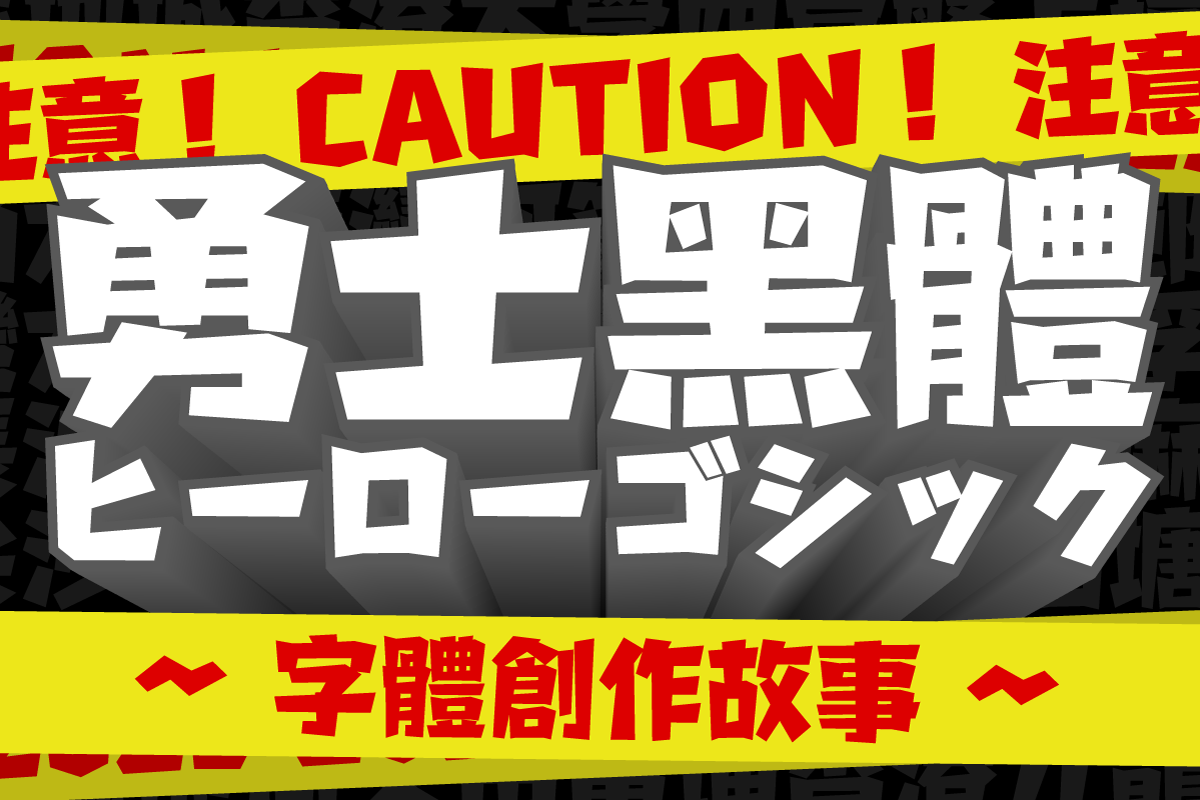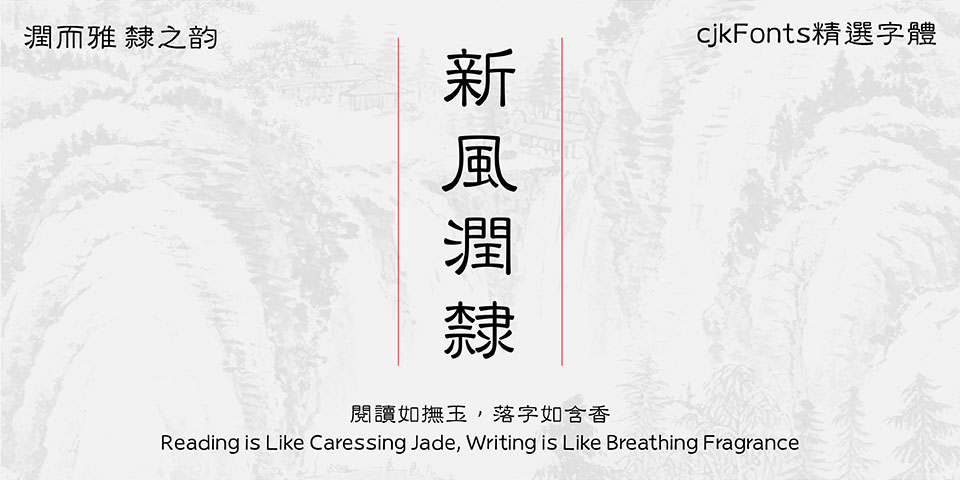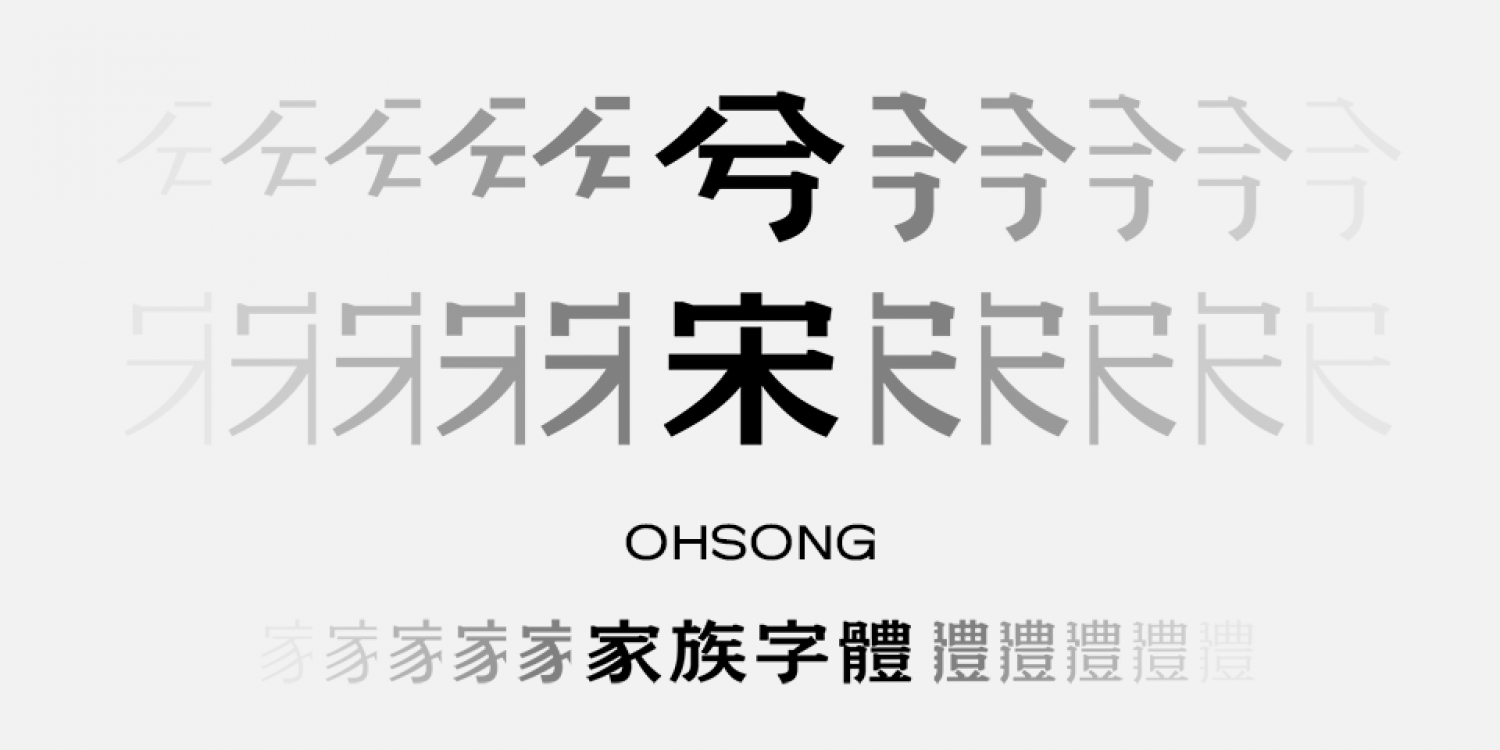
新風潤隸 - 閱讀如撫玉,落字如含香
兮宋家族字體計劃
字言字型免費中文字體1—手繪體
字體採用了手繪塗鴉風格,並以宋體的筆形配上楷體的骨架製成,營造出不同於其他單一風格的造型。
隨峰體Plus
cjkFonts的字型設計師以隨峰體爲基礎,整合不同的衍生版本,並再添補和修訂,製作發佈爲「隨峰體Plus」
隨峰體
簡介 : 逐字逐字以啫喱筆寫成的手寫字體,而且保留手寫痕跡和瑕疵。
cjkFonts 手寫4
簡介 : 基於清松手寫體4透過深度學習智能造字, 免費可商業用途。
cjkFont 全瀨體
簡介 : 基於瀨戶字體透過深度學習智能造字,支持繁中、簡中、日及韓 免費可商業用途。
字言字型免費中文字體1—手繪體
字體採用了手繪塗鴉風格,並以宋體的筆形配上楷體的骨架製成,營造出不同於其他單一風格的造型。
《勇士黑體》創作故事-從遊戲中汲取靈感
謝謝您來看這篇文章,我是《勇士黑體》的主創設計劉岑群。要說字體是我的第二個生命,電子遊戲則是第三個。我酷愛玩單機電子遊戲,也愛從遊戲中尋找靈感。各種種類都玩一些,儘管大多數類型的遊戲都玩的挺菜的。
隨峰體Plus
cjkFonts 的字型設計師以「隨峰體」原檔案爲基礎,整合不同的衍生版本,並再添補和修訂使用者有需求的字,把新製作成果發佈作「隨峰體Plus」。